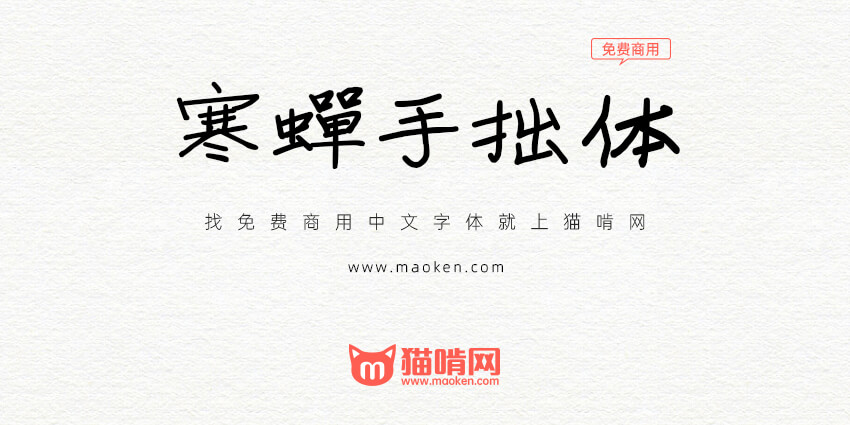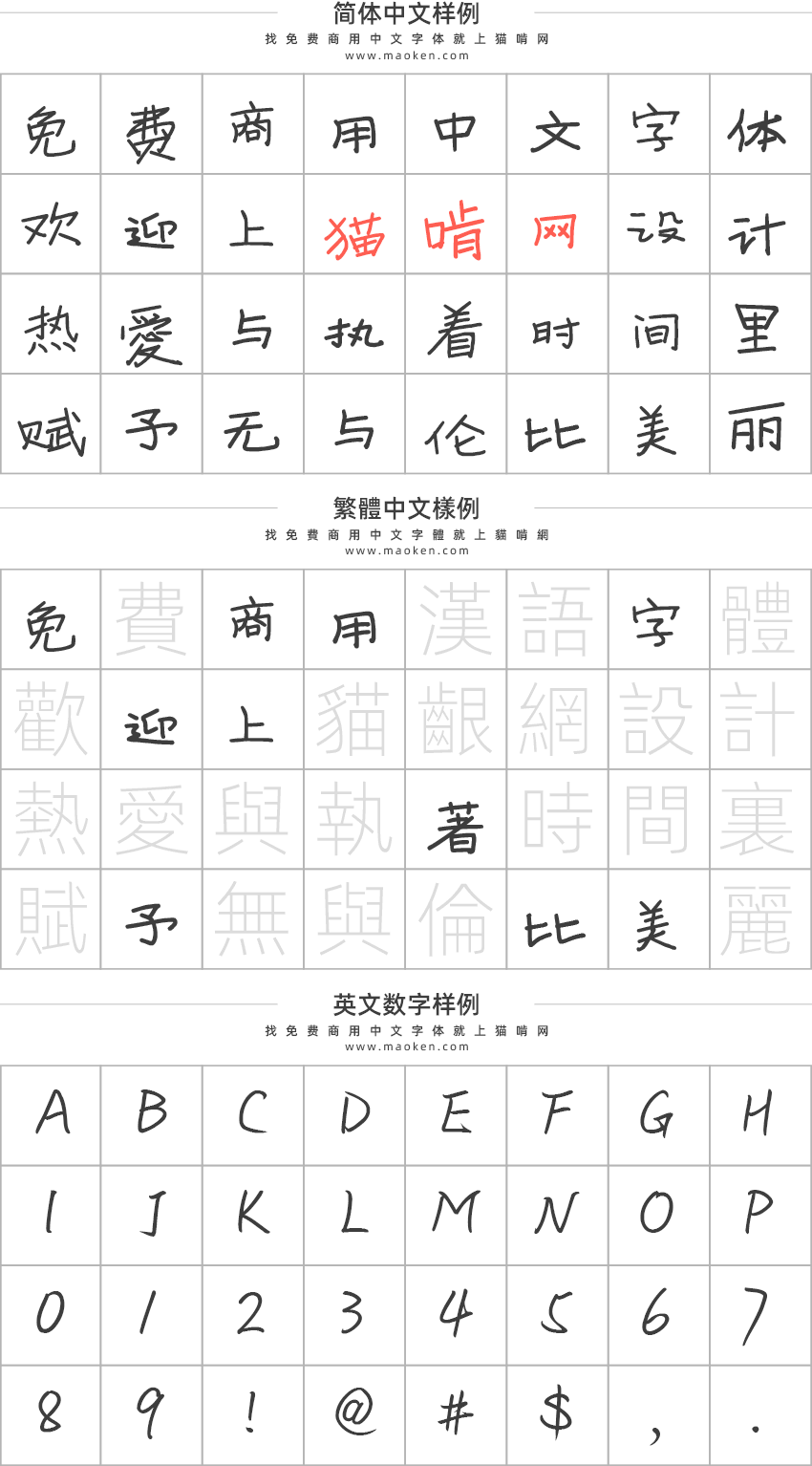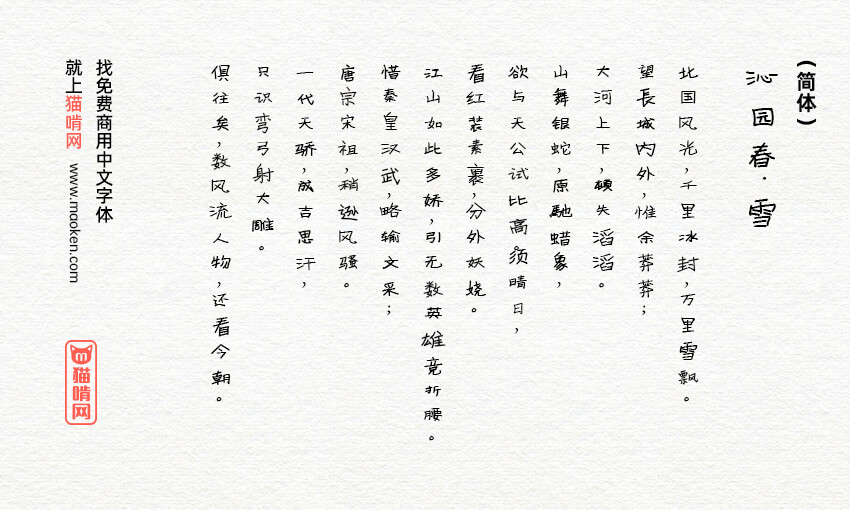
寒蝉手拙体:发掘手写字体的手拙之美 免费商用
字体作者:萧熠Siue (中国大陆) 字体字重:1个
寒蝉手拙体,主要精髓为发掘手写字体的手拙之美,字体给人一种逼真手写的视觉体验。虽应用范围有限,但有其不可替代和独特的价值。以创造的笔意和结构完成,形成风格独特的一套小众字体。
• 优化竖排文字,新增若干标符。
• 修正了部分简体显示为繁体的问题,更符合标准。
• 补充GB2312字符数标准缺失文字。
• 修正字体重心位置,字符排列更加整齐。
• 更新了部分文字忽高忽低的问题。使整体视觉更加平衡。
• 重写了英文标点符号问题。